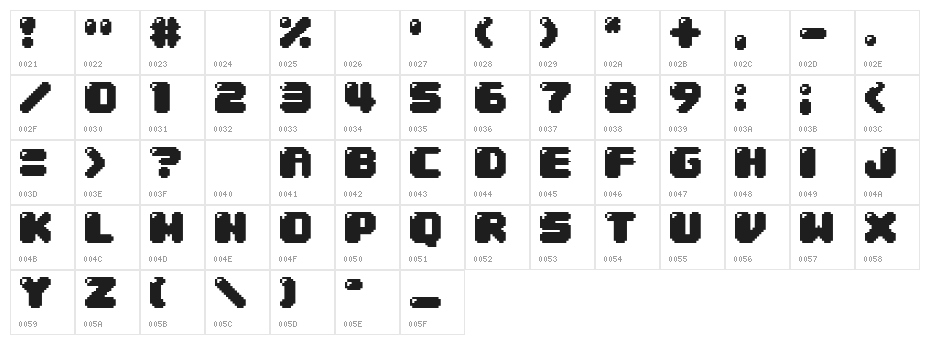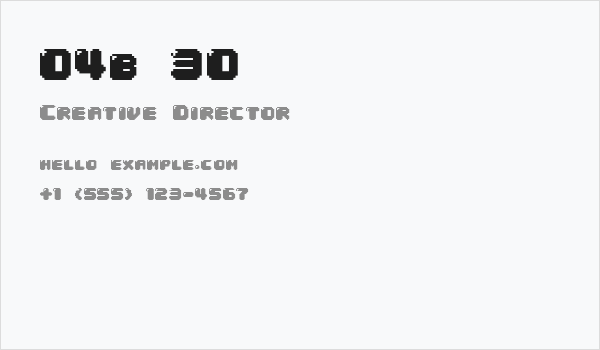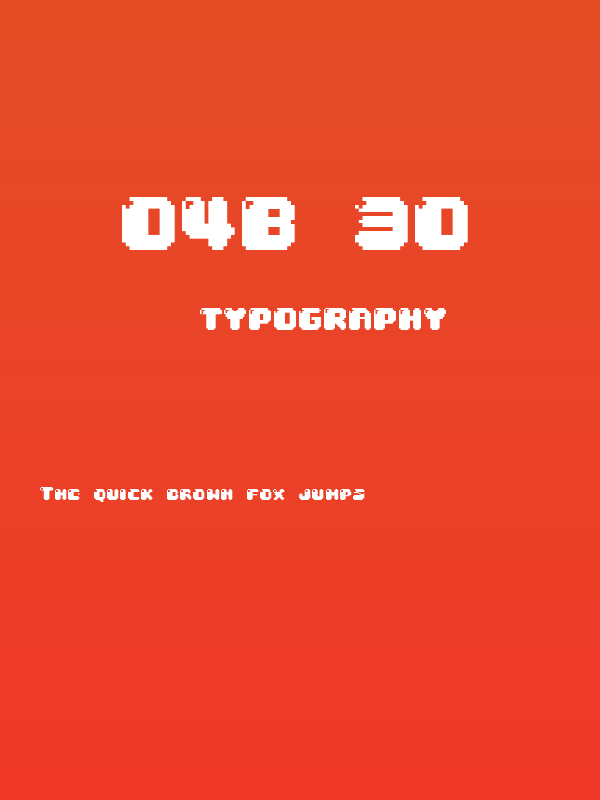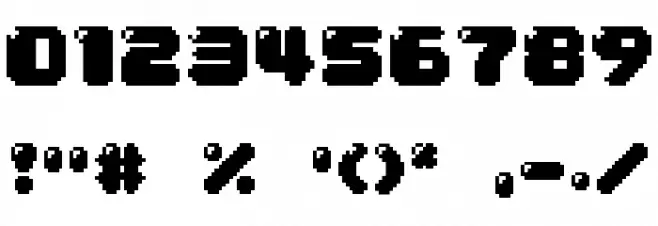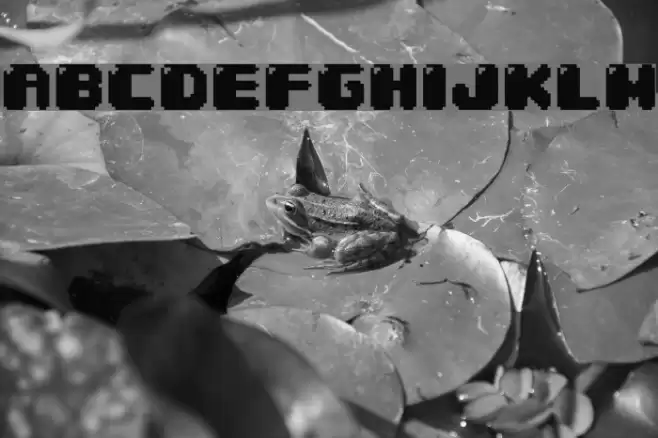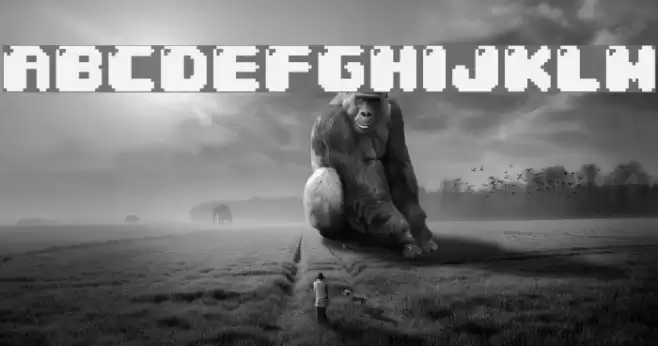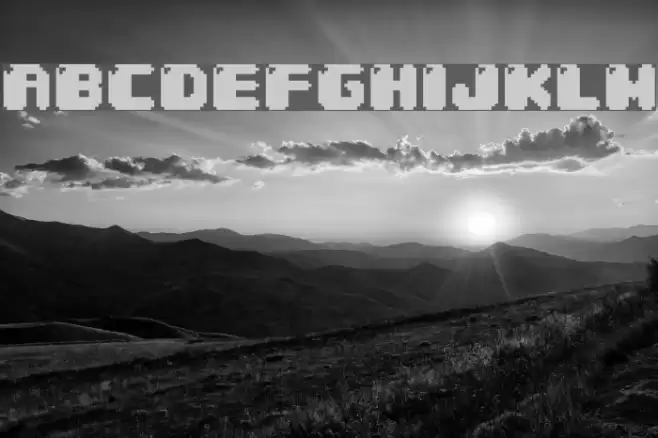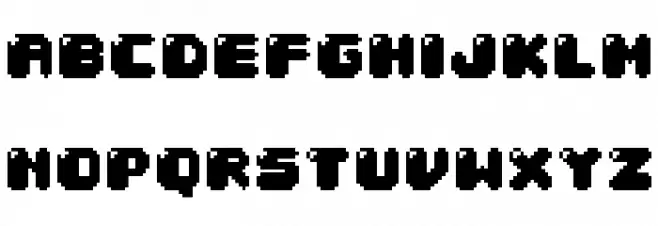
04b 30 Font
| Estilo general | Retro, Digital |
| Caso de uso | Logos, Posters, Video games |
| Proyectos propuestos | Ideal for projects that require a vintage digital aesthetic, such as retro video games, tech-themed posters, or digital art displays. |